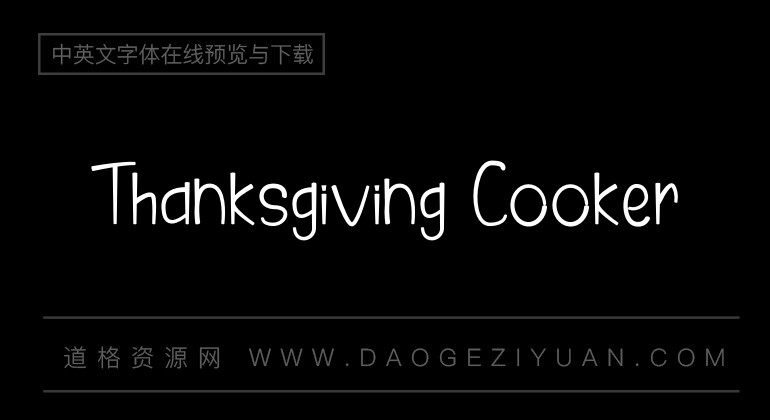
Thanksgiving Cooker字体是一款经典的节日字体,它是专门为庆祝感恩节而设计的,具有明亮、复古、可爱的特点,可以在印刷品、海报、海报、T恤、杂志封面、礼品卡等上使用。它具有清晰的轮廓,宽阔的字体,以及温暖的色调,可以使人们感受到温暖的庆祝气氛。内容介绍
Thanksgiving Cooker是一款非常不错的手写艺术字体,具有很好的视觉感,适合于文化类的宣传设计、商业类品牌的广告和产品包装设计以及个性化文字排版等较多场景。